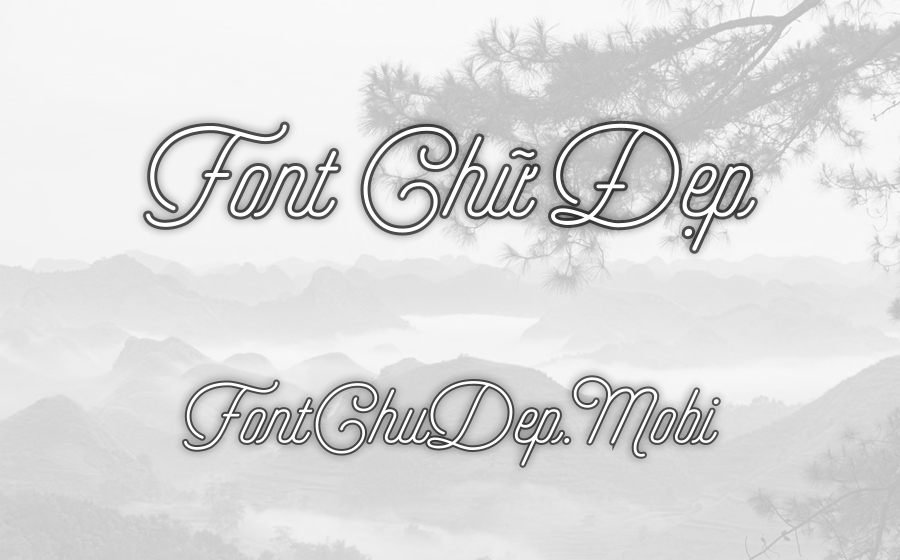
Font VL Selfie Việt Hóa
VL Selfie Regular
Thật không ngoa khi nói rằng VL-Selfie-Regular là một phông chữ tuyệt vời với vẻ đẹp của thư pháp hiện đại. Được tạo ra bởi Maximiliano R. Sproviero, font chữ này gây ấn tượng mạnh với tôi nhờ vào sự cân đối hoàn hảo giữa nét cổ điển và hiện đại. Những đường nét uyển chuyển, mềm mại của nó làm cho thiết kế trở nên đặc biệt hơn bao giờ hết.
Một trong những tính năng nổi bật là khả năng hoà hợp với nhiều ứng dụng khác nhau. Từ những tấm thiệp mời, poster quảng cáo đến thiết kế logo hay tiêu đề sách, VL-Selfie-Regular đều có thể tạo nên dấu ấn riêng. Đặc biệt, với sự Việt hóa từ Việt Linh, font chữ này hỗ trợ đầy đủ các ký tự tiếng Việt, mang lại trải nghiệm thoải mái và thuận tiện cho những người thiết kế tại Việt Nam.
Tôi cảm thấy rất hài lòng khi FontChuDep.mobi sở hữu và chia sẻ phông chữ này, bởi nó không chỉ đáp ứng nhu cầu thiết kế đa dạng mà còn mang đến cơ hội sáng tạo vô hạn. Dù là trong các sự kiện như thiệp cưới, lễ hội hay sinh nhật, hay trong những ngành nghề sáng tạo như quảng cáo, ẩm thực, spa và nhiếp ảnh cưới, VL-Selfie-Regular đều thể hiện sự duyên dáng và tính linh hoạt tuyệt vời.
Trải nghiệm của tôi với VL-Selfie-Regular thực sự ấn tượng và tôi tin rằng nó sẽ tiếp tục là nguồn cảm hứng vô tận cho những dự án thiết kế của bạn.